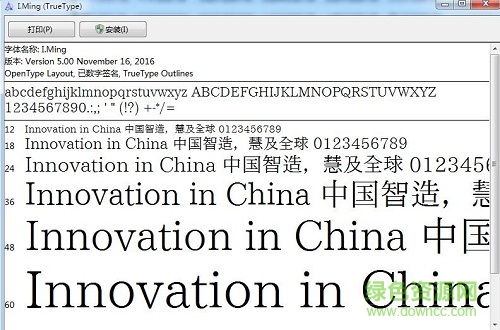
刻石錄明體字體是一款經(jīng)過精心設(shè)計(jì)之后的一款字體,字體的豎向線條較粗,橫向較細(xì),非常適合用作于印刷等行業(yè),有需要的朋友歡迎下載使用!
刻石錄明體字型衍生自林隆男所設(shè)計(jì)的兩款字形TB明體和TB黑體,字型包含了日本常用的字元,以供日本人使用!